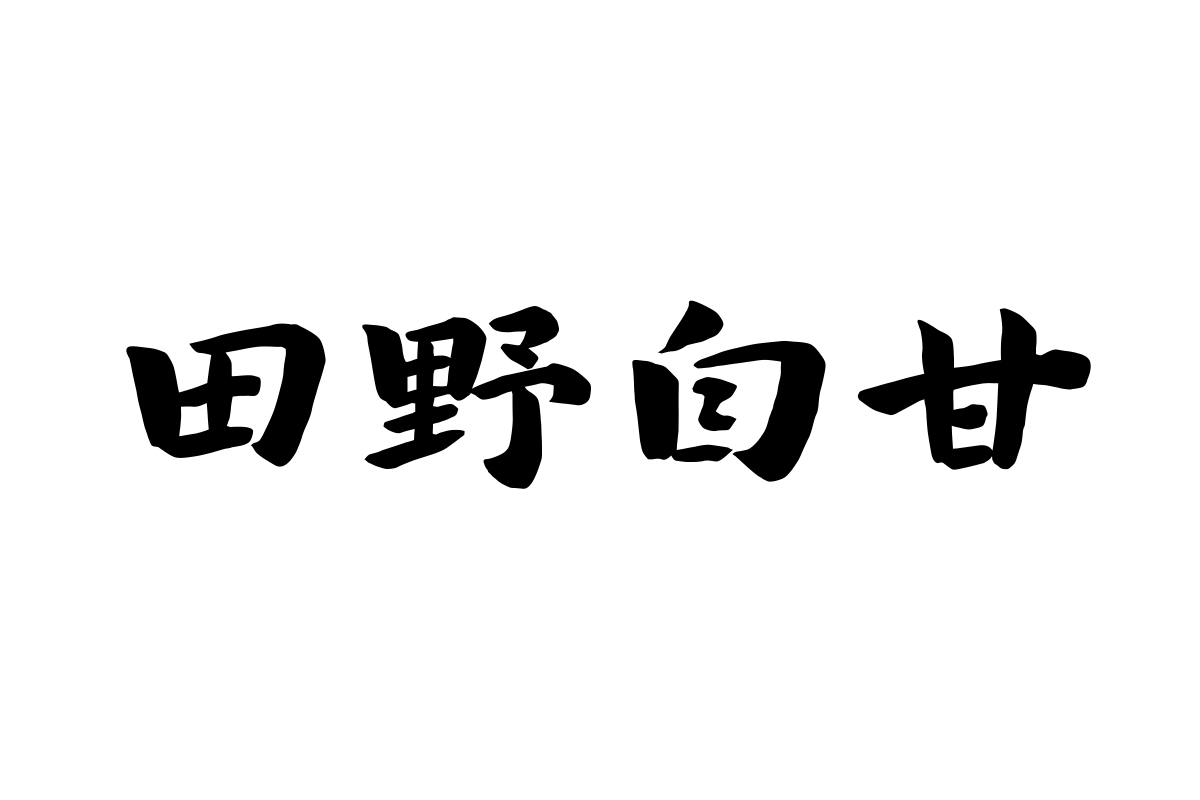
汉仪杰龙古楷繁体字体是一款具有独特风格的书法字体,它融合了传统书法的韵味和现代审美的元素。这款字体的特点是笔画流畅、结构严谨,给人以古朴典雅的感觉。它的字形特点主要体现在以下几个方面:
1. 笔画圆润饱满:汉仪杰龙古楷繁体字体的笔画线条圆润饱满,给人一种稳重而大气的感觉。这种笔画的特点使得字体在视觉上更加和谐,易于阅读和识别。
2. 结构紧凑有序:这款字体的结构紧凑有序,每个字的笔画都经过精心设计,使其在有限的空间内呈现出丰富的变化。这使得字体在视觉上具有很强的层次感和立体感,增加了字体的艺术性。
3. 风格古朴典雅:汉仪杰龙古楷繁体字体的风格古朴典雅,充满了浓厚的文化气息。它适合用于需要展现传统文化韵味的场合,如书籍、杂志等。这款字体的运用可以提升作品的整体格调,使读者感受到中国传统文化的魅力。
4. 可读性强:汉仪杰龙古楷繁体字体在保持美观的同时,也注重可读性。它的笔画粗细适中,间距合理,使得字体在快速阅读时依然清晰易辨。这使得这款字体在实际应用中具有较高的实用价值。
总的来说,汉仪杰龙古楷繁体字体是一款具有独特风格的书法字体,它融合了传统与现代的元素,展现出古朴典雅的艺术魅力。无论是用于书籍、杂志还是其他媒体,这款字体都能为作品增添一份独特的韵味。